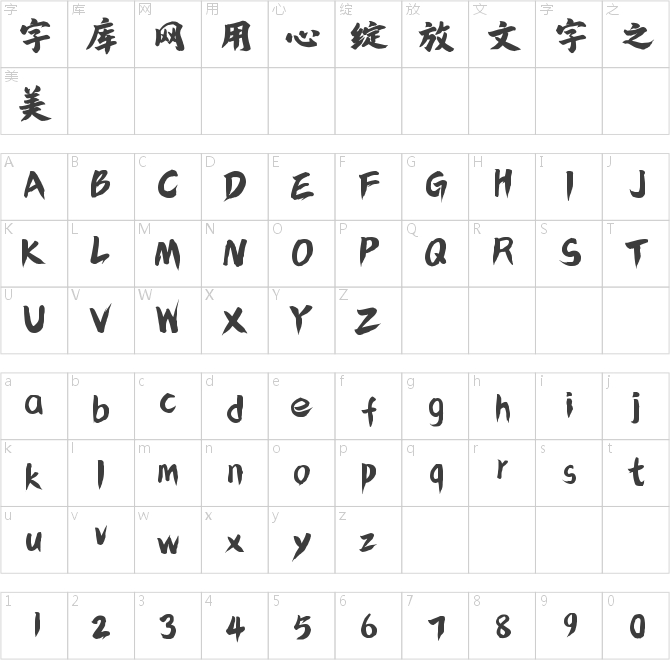
字魂220號-鴻雁手書 詳情頁
字魂220號-鴻雁手書是一款書法字。字形結(jié)構(gòu)飽滿,雍容大氣,字體筆畫圓渾厚重,字體的風(fēng)格渾厚雄放,適用于產(chǎn)品包裝和宣傳設(shè)計(jì)。
字魂220號-鴻雁手書字體zihun220hao-hongyanshoushu字庫是一款讓人賞心悅目、百看不厭的中文字體,適合各類廣告和產(chǎn)品包裝設(shè)計(jì)應(yīng)用,字體大小9.17MB,格式為ttf字體,上傳用戶是手機(jī)洗相,作者/版權(quán)方為字魂